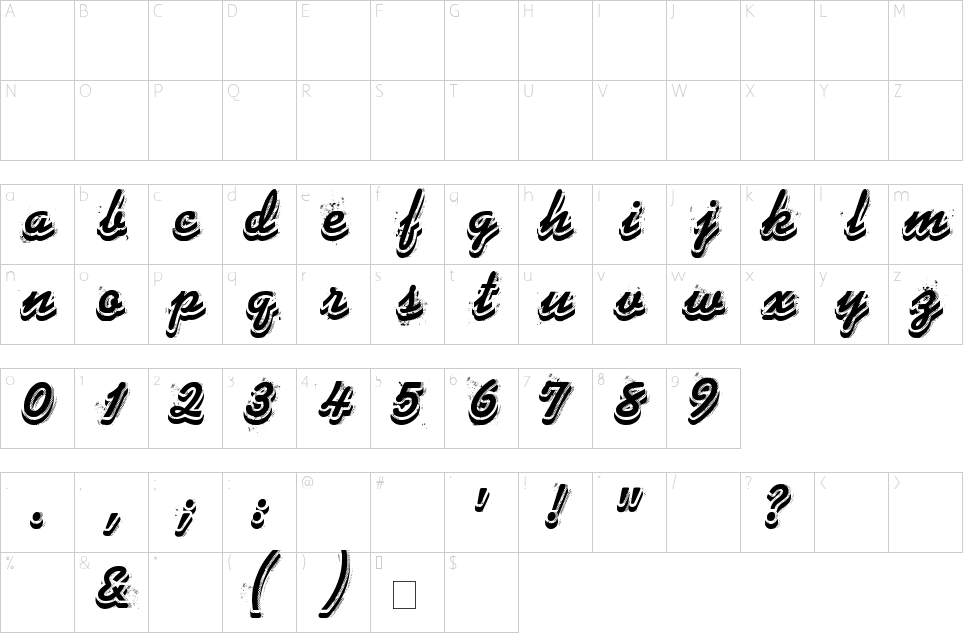
A fonte Phonograff é uma grata surpresa para designers e criadores de conteúdo de todo o mundo. Desenvolvida por Segments Design (antigo Last Soundtrack), esta fonte está disponível de graça tanto para sistemas Windows quanto para Mac. O design delicado e elegante de Phonograff oferece uma variedade de opções de estilo que podem se adaptar a qualquer projeto de design, sejam eles empreendimentos digitais, trabalhos de blog, designs de site ou até mesmo trabalhos gráficos de arte. Com seu design agradável e sofisticado, Phonograff não apenas oferece uma solução de fonte gratuita, mas também uma opção de qualidade que muitas vezes é encontrada em versões pagas. Desde que foi lançada, a fonte Phonograff tem sido popular entre os designers, e já foi baixada mais de 6.350 vezes. Para os que buscam uma solução de fontes de alta qualidade de forma gratuita, a fonte Phonograff é uma ótima escolha.